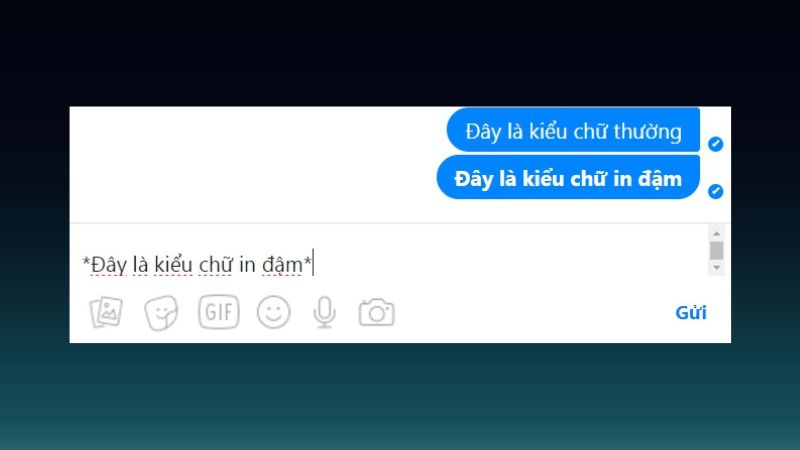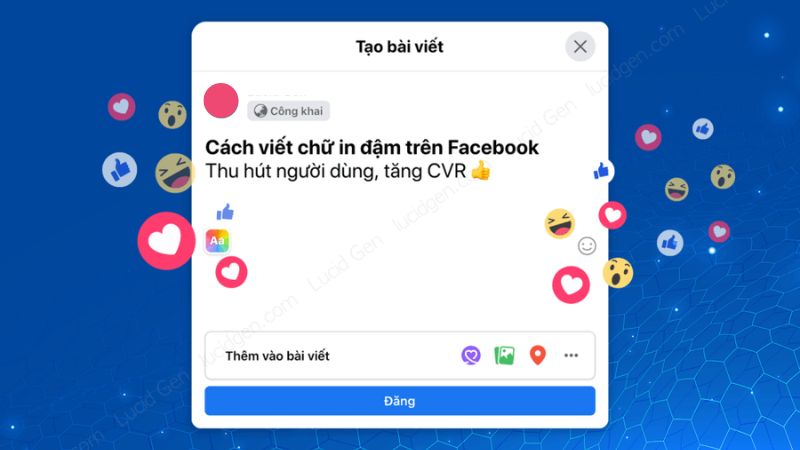
Top 5 cách in đậm chữ Facebook không lỗi font hiệu quả nhất
In đậm chữ Facebook không lỗi font
Bạn đang viết bài đăng Facebook và cần in đậm chữ nhưng chưa biết cách? Bạn làm theo cách thông thường nhưng bài đăng bị lỗi hiển thị hoài? Đừng lo, trong bài viết này, Điện thoại Giá Kho sẽ giới thiệu tới bạn 5 cách in đậm chữ Facebook không lỗi font hiệu quả nhất. Hãy cùng theo dõi ngay sau đây nhé.
Ưu điểm của việc in đậm chữ Facebook
Facebook là một ứng dụng mạng xã hội được thiết lập với font chữ thông thường. Việc nhìn một font chữ lâu ngày sẽ dẫn đến sự nhàm chán và không thu hút người xem. Vì vậy, khi in đậm chữ lên sẽ giúp bạn ghi đậm dấu ấn vào bài đăng của mình. Hơn nữa còn mang đến một sắc thái hoàn toàn mới, gây được hiệu mạnh vào một số việc nhất định như:
Ưu điểm của việc in đậm chữ Facebook
Tiêu đề thu hút
In đậm chữ Facebook sẽ giúp tiêu đề của bài đăng hay giao diện trở nên thu hút, hấp dẫn và thú vị hơn.
Được nhiều người chú ý tới
Khi sử dụng in đậm chữ Facebook không bị lỗi font trong bình luận sẽ khiến ý kiến của bạn được nổi bật giữa đồng người. Nhờ đó mọi người có thể chú ý tới sự xuất hiện của bạn. Và biết tới bạn nhiều hơn. Gia tăng sự nhận diện thương hiệu cho bạn trong kinh doanh.
Tạo hiệu ứng quảng cáo
Nếu bạn là một người bán hàng online hoặc một thương hiệu đang kinh doanh trên nền tảng Facebook. Việc lên bài content làm sao để thu hút nhiều người nhất là một việc rất quan trọng. Và rõ ràng, với những font chữ in đậm sẽ giúp cho bài đăng của bạn khác biệt so với những bài còn lại. Hơn nữa còn gây hiệu ứng mạnh mẽ, khơi gợi sự ham muốn tìm hiểu của người tiêu dùng. Và sản phẩm cũng như thương hiệu của bạn sẽ được chú ý tới nhiều hơn.
Tạo hiệu ứng quảng cáo
Nhấn mạnh thông báo
Với những thông báo mang tính quan trọng, gấp rút, việc in đậm sẽ khiến thông báo được nhấn mạnh. Và người xem sẽ nhận thức được tầm quan trọng của thông báo này.
Thế nhưng nếu chỉ in đậm bằng cách thông thường sẽ khiến bài đăng của bạn bị lỗi. Vậy phải làm sao để in đậm chữ Facebook không lỗi font?
Top 5 Cách in đậm chữ Facebook không lỗi font
Việc in đậm chữ Facebook thì có rất nhiều cách. Và ngay sau đây, không để bạn chờ lâu thêm, Điện thoại Giá Kho sẽ giới thiệu tới bạn 5 cách in đậm chữ Facebook không bị lỗi font hiệu quả và an toàn nhất. Hãy cùng theo dõi nhé.
Cách in đậm chữ Facebook không lỗi font bằng Messenger
Để sử dụng chữ in đậm trong các văn bản messenger hay sử dụng trong bình luận. Bạn thực hiện ký hiệu nhanh bằng cách:
Sử dụng Messenger
• In đậm chữ: Gõ cú pháp *nội dung bạn muốn in đậm*
• Tạo chữ nghiêng: Gõ cú pháp _nội dung bạn muốn làm nghiêng_
• Tạo chữ vừa in đậm và nghiêng: Gõ tổ hợp cú pháp -*nội dung bạn muốn in đậm và làm nghiêng*_
• Chữ có dấu gạch ở giữa: Gõ cú pháp ~nội dung bạn muốn gạch~
Lưu ý quan trọng
cách này chỉ hiệu quả đối với những bạn sử dụng Messenger trên máy tính. Khi bạn sử dụng trên điện thoại, tất cả những kí hiệu sẽ hiển thị theo và chữ vẫn sẽ ở trạng thái cơ bản.
Cách in đậm chữ Facebook không lỗi font trong Group
Đối với các nhóm Group trên facebook, bạn có thể thực hiện việc này theo một cách đơn giản hơn nhiều. Những gì bạn cần chỉ là bôi đen chọn phần văn bản bạn muốn chỉnh sửa kiểu font. Lúc này một menu Formet sẽ hiện ra. các biểu tượng sẽ xuất hiện. Bạn nhấn vào các biểu tượng để chuyển đổi câu của mình sang font chữ bạn muốn:
• Biểu tượng B (Crtl + B): in đậm